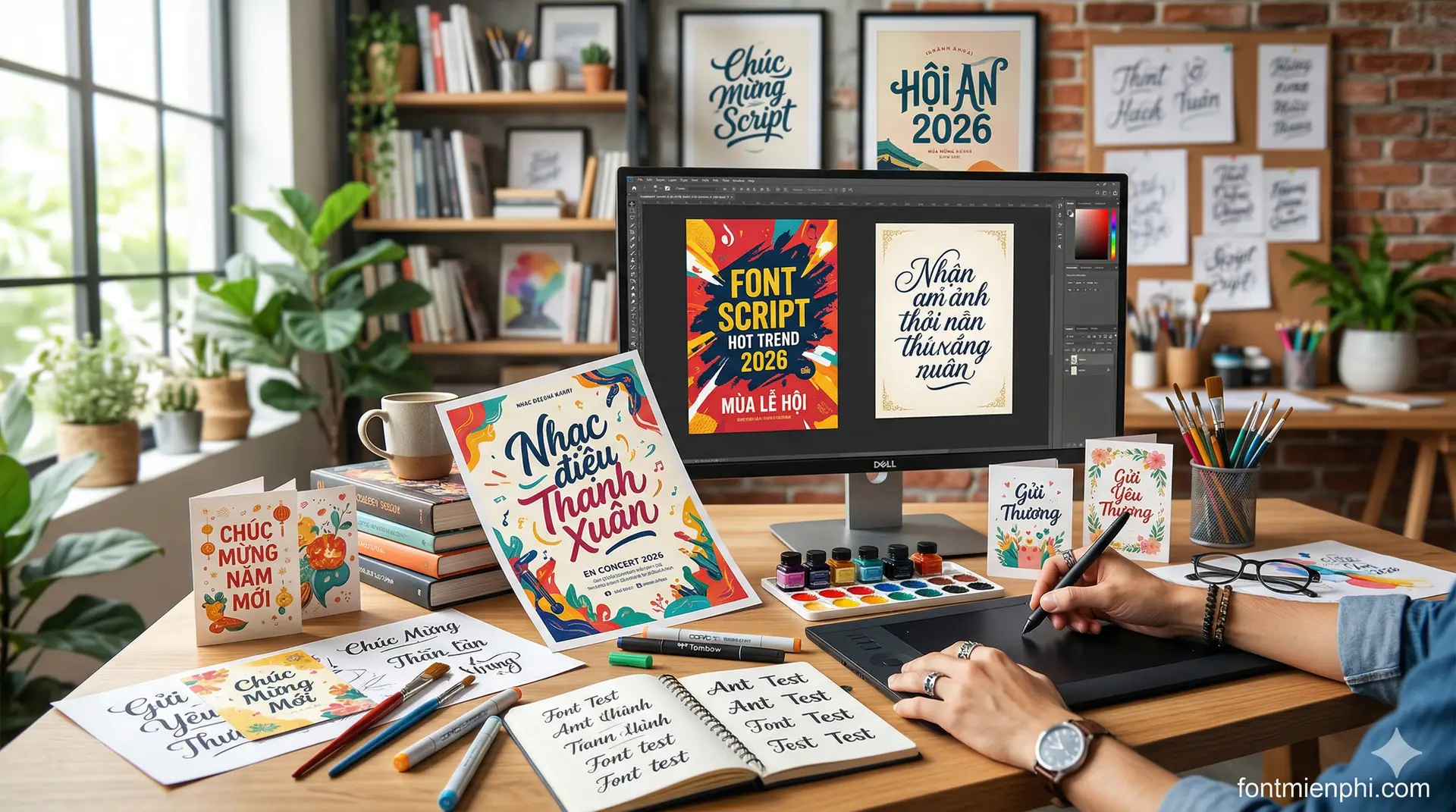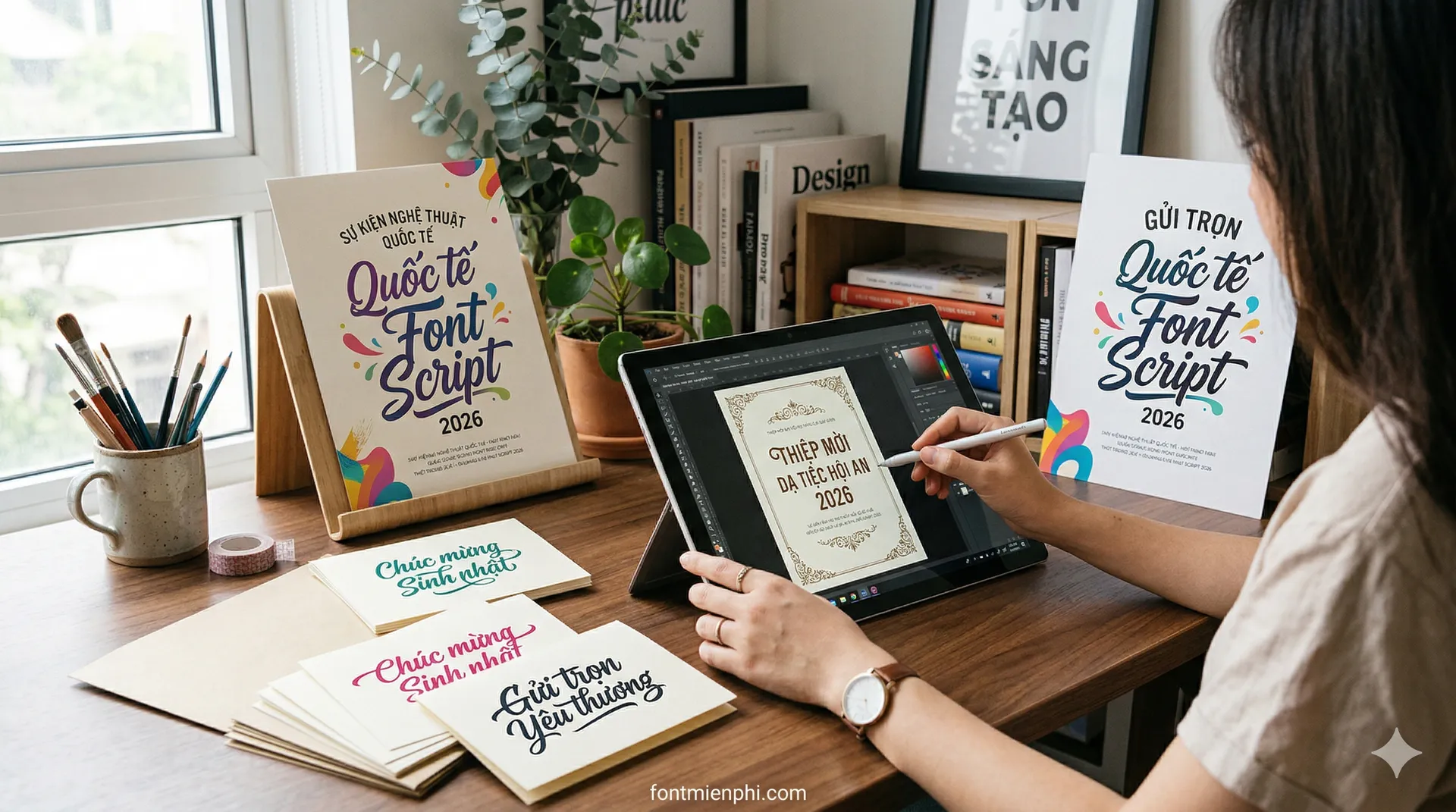
Bài viết này tổng hợp và phân tích chuyên sâu về những xu hướng font chữ dạng viết tay (Script) đã được Việt hóa hoàn chỉnh, dự kiến sẽ thống trị ngành thiết kế đồ họa trong năm 2026. Chúng ta sẽ cùng khám phá các đặc điểm thẩm mỹ, khả năng ứng dụng thực tế trên thiệp mời, poster sự kiện và cách lựa chọn font chữ phù hợp để tối ưu hóa trải nghiệm thị giác.
Top Font Script Việt Hóa Hot Trend 2026 Dành Cho Thiết Kế Thiệp Và Poster
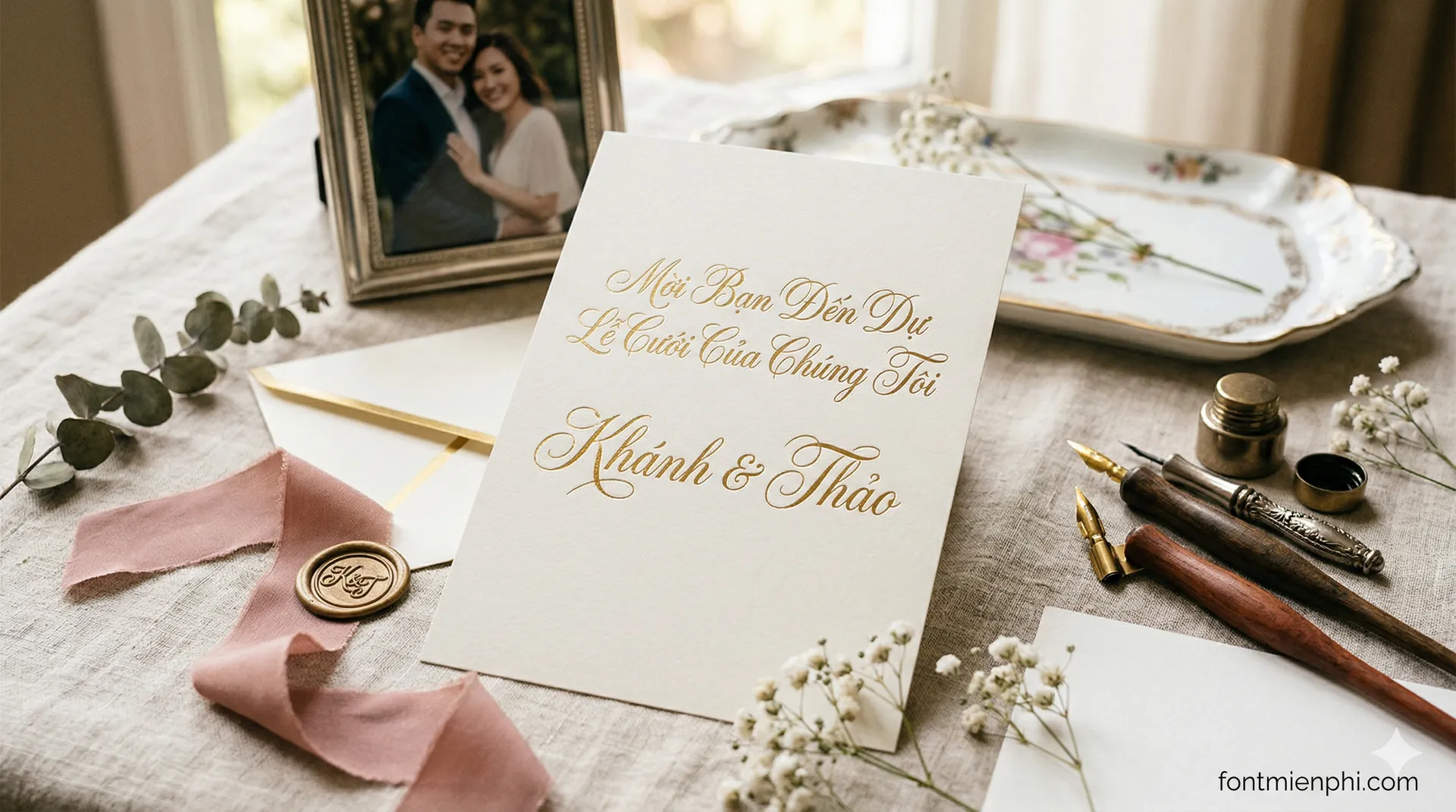
Trong thế giới thiết kế đồ họa đang chuyển mình mạnh mẽ, sự cá nhân hóa và tính thủ công đang trở thành những giá trị cốt lõi. Năm 2026 đánh dấu sự lên ngôi của các dòng font Script với những đường nét uyển chuyển, mang đậm dấu ấn cá nhân nhưng vẫn đảm bảo tính kỹ thuật tối ưu cho các nền tảng kỹ thuật số và in ấn. Đối với các nhà thiết kế thiệp cưới, thiệp mời sự kiện hay poster quảng cáo, việc nắm bắt các mẫu font Script Việt hóa mới nhất không chỉ giúp tác phẩm trở nên hiện đại mà còn truyền tải được cảm xúc chân thực đến người xem.
Xu hướng thiết kế font chữ năm 2026
Trước khi đi sâu vào danh sách các font chữ cụ thể, cần hiểu rõ bối cảnh thẩm mỹ của năm 2026. Sau một thời gian dài ưu tiên phong cách tối giản (Minimalism) với các font không chân cứng nhắc, thị trường bắt đầu khao khát sự mềm mại và phóng khoáng.
Xu hướng Organic Fluidity: Các đường nét không còn tuân theo quy tắc đối xứng hoàn hảo. Thay vào đó là những nét vẽ mô phỏng lại chữ viết tay tự nhiên của con người với độ thanh đậm không đều, tạo cảm giác gần gũi.
Sự lên ngôi của Serif phối hợp Script: Việc kết hợp giữa một font chữ có chân cổ điển và một font Script bay bổng đang trở thành công thức chuẩn cho các thiết kế sang trọng.
Tối ưu hóa hiển thị (Screen Optimization): Các font Script hiện đại được thiết kế với độ dày nét hợp lý để không bị vỡ hoặc khó đọc khi hiển thị trên màn hình điện thoại có độ phân giải cao.
Danh sách các Font Script Việt hóa dẫn đầu xu hướng
Dưới đây là những bộ font chữ được tuyển chọn dựa trên tần suất xuất hiện trong các dự án sáng tạo quốc tế và đã được các đơn vị uy tín tại Việt Nam thực hiện Việt hóa kỹ lưỡng, đảm bảo không lỗi dấu tiếng Việt.
1. Font Heritage Signature Việt Hóa
Heritage Signature là biểu tượng của sự thanh lịch và đẳng cấp. Đây là mẫu font mô phỏng chữ ký tay chuyên nghiệp với những nét kéo dài (swashes) cực kỳ nghệ thuật.
Đặc điểm: Nét chữ mảnh, sắc sảo, có độ nghiêng vừa phải tạo cảm giác chuyển động.
Ứng dụng tốt nhất: Thiết kế thiệp cưới cao cấp, danh thiếp cá nhân cho các nhà sáng tạo hoặc tiêu đề chính trên các poster thời trang.
Lưu ý khi dùng: Vì nét chữ khá mảnh, nên sử dụng ở kích thước lớn hoặc đặt trên nền đơn sắc để tránh mất nét.
2. Font Better Saturday Việt Hóa
Nếu bạn đang tìm kiếm một cảm giác trẻ trung, năng động và có phần hơi nổi loạn, Better Saturday chính là lựa chọn hàng đầu cho năm 2026.
Đặc điểm: Cấu trúc chữ cái có độ cao không đồng nhất, các đường nối chữ được thực hiện một cách ngẫu hứng nhưng vô cùng hợp lý.
Ứng dụng tốt nhất: Poster các sự kiện âm nhạc, bìa sách cho giới trẻ, các mẫu thiệp chúc mừng sinh nhật mang phong cách hiện đại.
Ưu điểm: Bộ ký tự Việt hóa của font này xử lý các dấu như huyền, sắc, hỏi rất khéo léo, không làm phá vỡ cấu trúc tổng thể của chữ.
3. Font Mellow Morning Việt Hóa
Mellow Morning mang đến một hơi thở bình yên và nhẹ nhàng. Đây là dòng font Script có nét chữ tròn trịa hơn, tạo cảm giác thân thiện và ấm áp.
Đặc điểm: Độ tương phản giữa nét thanh và nét đậm không quá lớn, các góc chữ được bo tròn mềm mại.
Ứng dụng tốt nhất: Poster cho các chiến dịch vì cộng đồng, thiệp cảm ơn, hoặc các thiết kế liên quan đến ngành hàng chăm sóc sức khỏe, làm đẹp tự nhiên.
4. Font Rochester Script Việt Hóa
Đây là sự kết hợp hoàn mỹ giữa nét cổ điển của những thập niên trước và kỹ thuật đồ họa hiện đại. Rochester mang trong mình sự quý phái của các dòng chữ trong các bức thư tay thời xưa.
Đặc điểm: Chữ cái thẳng đứng hơn so với các dòng Script thông thường, tạo cảm giác vững chãi và đáng tin cậy.
Ứng dụng tốt nhất: Thiết kế thực đơn (menu) cho các nhà hàng sang trọng, poster phim lịch sử hoặc thiệp mời các buổi dạ tiệc.
Kỹ thuật lựa chọn và kết hợp font Script trong thiết kế
Sử dụng font Script không đơn thuần là chọn một kiểu chữ đẹp. Một chuyên gia thiết kế cần biết cách điều phối để font chữ phục vụ cho mục tiêu truyền thông của tác phẩm.
Nguyên tắc phân cấp thị giác (Visual Hierarchy)
Trong một poster, font Script thường được ưu tiên cho các tiêu đề chính (Headline) hoặc các từ khóa quan trọng muốn gây ấn tượng mạnh.
Tránh sử dụng font Script cho các đoạn văn bản dài hoặc thông tin chi tiết như địa chỉ, thời gian. Điều này sẽ gây mỏi mắt và giảm khả năng tiếp nhận thông tin của khách hàng.
Kết hợp với Sans Serif: Để tạo sự cân bằng, hãy kết hợp một font Script bay bổng với một font Sans Serif (không chân) đơn giản như Montserrat hoặc Roboto cho phần thông tin phụ.
Quản lý khoảng cách chữ (Kerning và Tracking)
Việc lựa chọn đúng font Script Việt hóa không chỉ là vấn đề thẩm mỹ, đó là cách bạn truyền tải linh hồn và thông điệp của sản phẩm đến với công chúng. Sự mềm mại của các nét chữ viết tay trong năm 2026 sẽ là cầu nối hoàn hảo giữa công nghệ số khô khan và cảm xúc chân thực của con người. Mong rằng danh sách và những phân tích chuyên sâu trên đây sẽ giúp ích cho quá trình sáng tạo của bạn trong những dự án sắp tới.